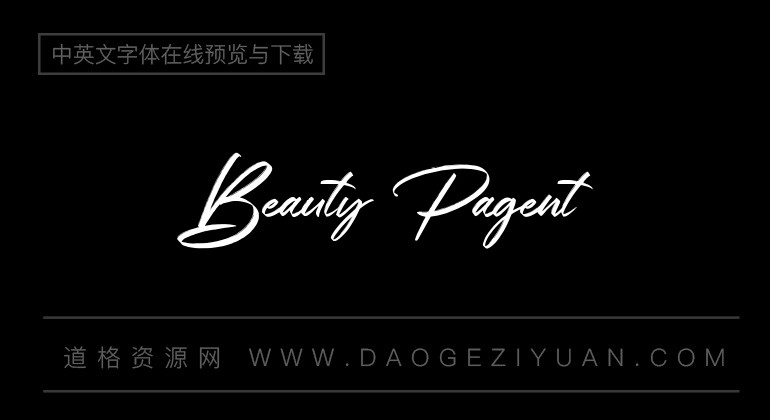
很抱歉,我认为您可能想说的是“Beauty Pageant”而不是“Beauty Pagent”字体。 Beauty Pageant 字体是一种优美和时尚的手写字体,具有柔和的连笔和流畅的线条。它看起来非常女性化和优雅,适用于许多类型的设计项目,例如品牌标识、海报、包装设计、印刷品、电子邮件、博客和社交媒体等。 Beauty Pageant 字体有两种风格:一种是正常的字体风格,另一种是斜体风格。它包括大写字母、小写字母、数字和标点符号,可以用于英语和其他一些拉丁字母语言。 总的来说,Beauty Pageant 字体是一种非常适合要求优雅和女性化的设计项目的字体。内容介绍
Beauty Pagent是一款非常不错的手写艺术字体,具有很好的视觉感,适合于文化类的宣传设计、商业类品牌的广告和产品包装设计以及个性化文字排版等较多场景。